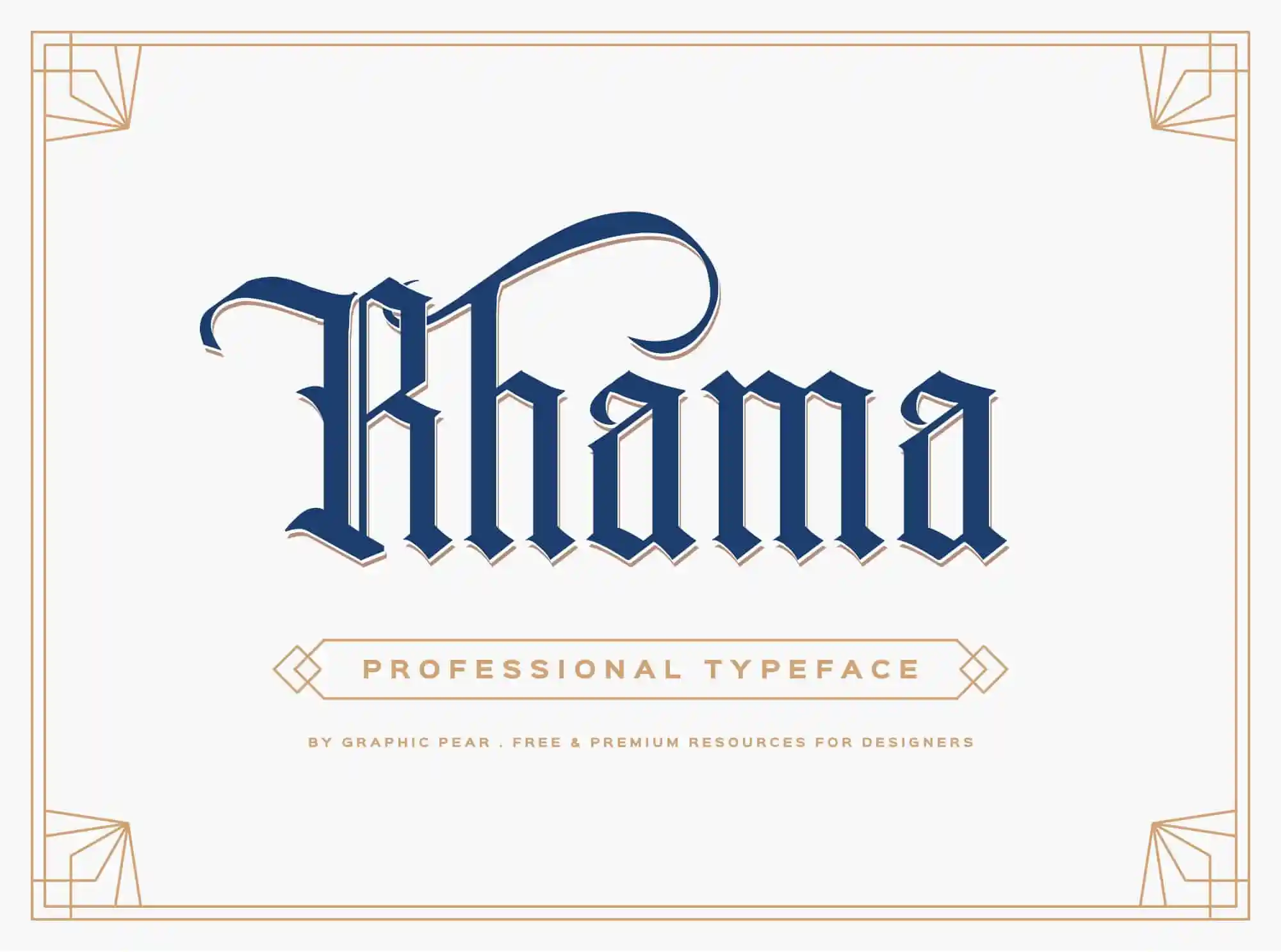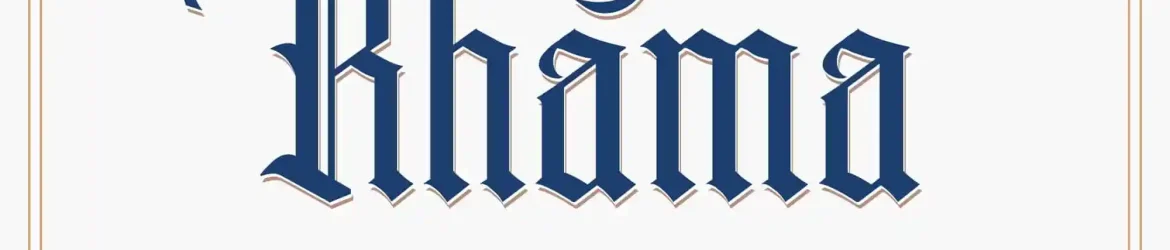
Rhama Typeface – Download Grátis
Introduzimos Rhama Typeface! Este tipo de fuso foi projetado e compartilhado pelo Graphicpear. É uma tipografia gothic, inspirada no estilo clássico. Rhama Gothic é um tipo tradicional de letra gótica, o que o torna perfeito para qualquer projeto que precise dessa característica. Rhama Typeface não apenas apresenta linhas robustas e elegantes em seu design original, mas também oferece uma linguagem sólida e forte que se destaca quando usada em projetos que exigem um tom sombrio ou antiquado. Este tipo é perfeito para adicionar um toque intrigante a qualquer projeto de identidade visual, desde logotipos até letras em jornais antigos. Com sua riqueza estilística e robustez, Rhama Typeface é uma ótima opção para quem procura incorporar um elemento distintivo em seus projetos visuais.